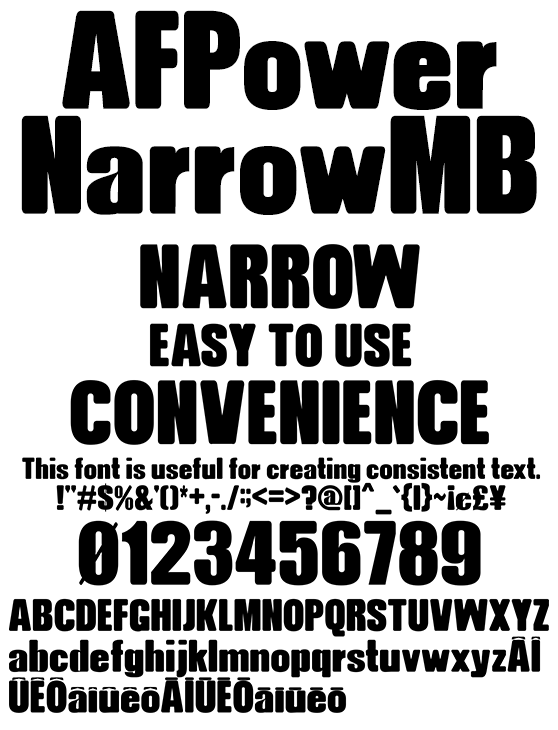
長体太字欧文 AFPowerNarrowMB
AFPowerNarrowMB
長体太文字欧文フォントです。「AFPowerMB.ttf」を長体にしました。レングスあるキーワードでも左右圧縮したフォントでインパクトある表現を維持できるでしょう。同人系、コミック、アニメ、ゲーム、リーフレット、フライヤー、ファッション系コンテンツに使える便利なフォントです。